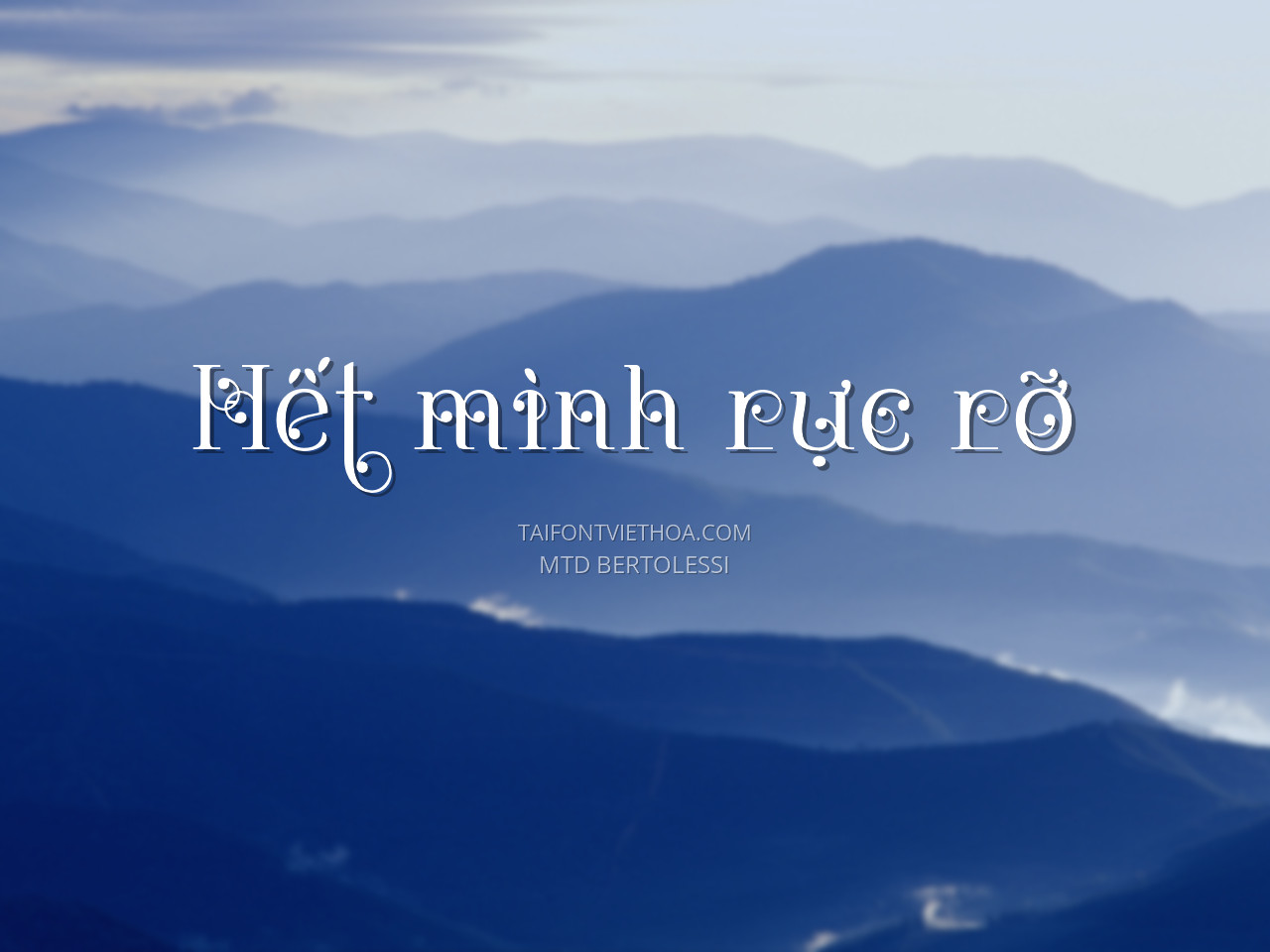
Font việt hóa MTD Bertolessi
Tác giả Font: Greater Albion Typefounders
Giới thiệu về font Bertolessi – Vẻ đẹp hoài cổ đậm chất Ý với cấu trúc serif sang trọng
Bertolessi là một kiểu chữ serif cổ điển mang phong cách châu Âu, đặc biệt lấy cảm hứng từ các bảng chữ in và kiến trúc nước Ý thế kỷ 19. Font có cấu trúc thanh thoát, các chi tiết serif được chăm chút tinh xảo với độ dày – mảnh đan xen tạo nên vẻ sang trọng, quý phái nhưng vẫn giữ được sự hiện đại trong trình bày. Bertolessi thường được ứng dụng trong các thiết kế liên quan đến thời trang, mỹ phẩm cao cấp, biên tập tạp chí hoặc nhận diện thương hiệu lịch thiệp. Font hỗ trợ hệ ký tự Latin mở rộng và hơn 60 ngôn ngữ.
Đặc điểm thiết kế cổ điển tinh tế và các ứng dụng lý tưởng của Bertolessi
Bertolessi sở hữu cấu trúc serif thanh mảnh, nét chữ cao, khoảng cách ký tự hợp lý giúp bố cục tổng thể trở nên thanh thoát và thoáng mắt. Các đầu chữ có chân được bo nhẹ, tạo cảm giác mềm mại, trong khi thân chữ vẫn giữ sự nghiêm túc và vững chãi. Font có độ tương phản cao giữa các nét, làm nổi bật nội dung tiêu đề và tên thương hiệu một cách hiệu quả.
Font phù hợp với các thiết kế như: tiêu đề sách văn học, poster thời trang, bộ nhận diện thương hiệu cao cấp, thiết kế mỹ phẩm thiên nhiên, menu nhà hàng sang trọng hoặc brochure nghệ thuật. Ngành nghề lý tưởng gồm: thời trang, mỹ phẩm, ẩm thực cao cấp, xuất bản, nội thất, nghệ thuật – thiết kế sáng tạo hoặc các thương hiệu cần truyền tải vẻ đẹp thanh lịch và tinh tế.